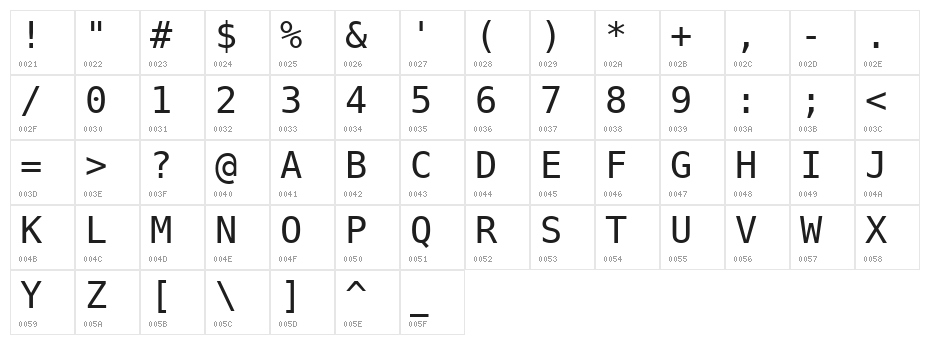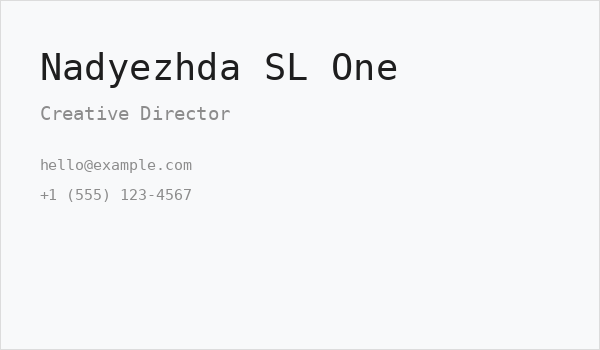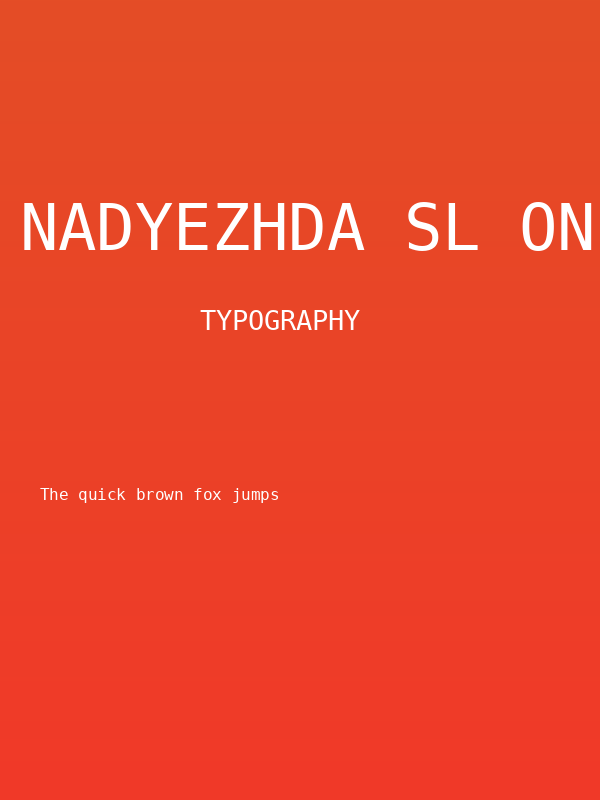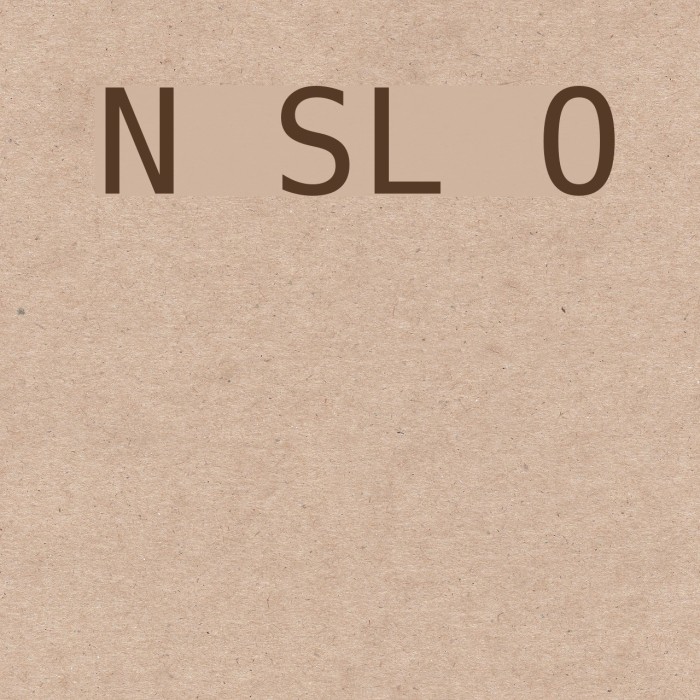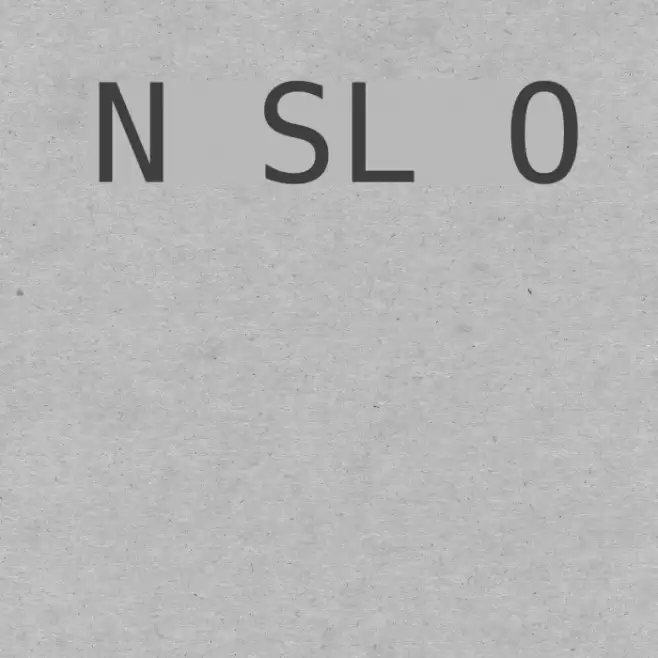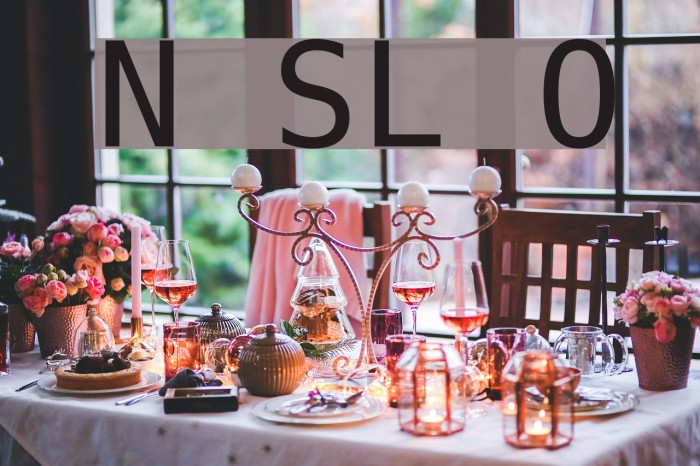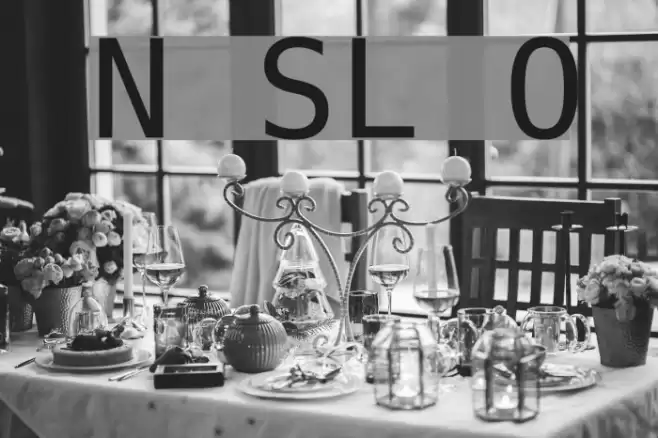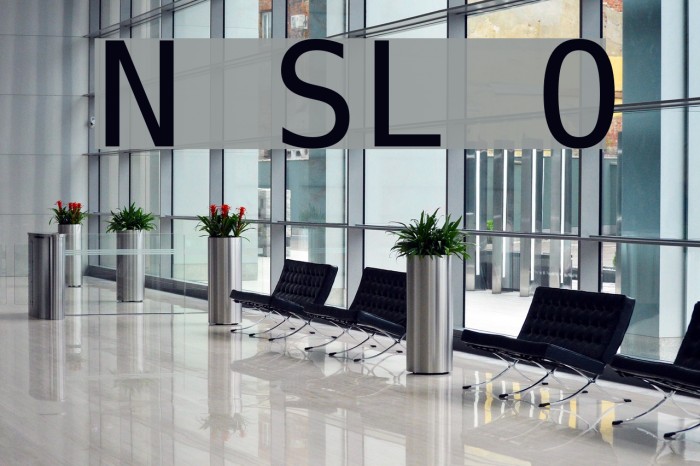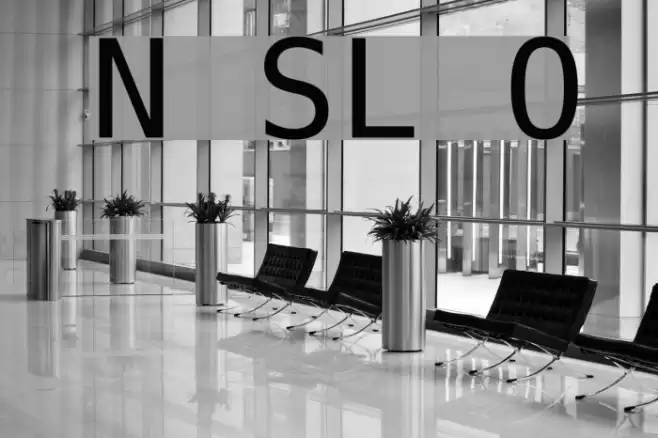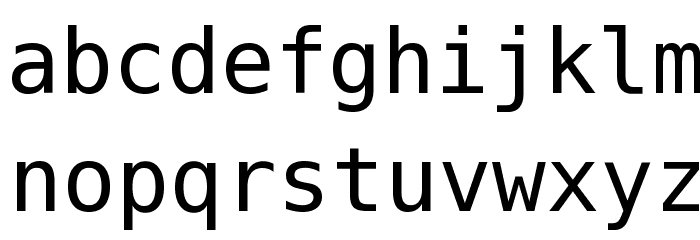
Nadyezhda SL One Font
| Anwendungsfall | Headlines, Body text, Logos |
| Vorgeschlagene Projekte | Ideal for corporate branding, web design, user interfaces, and print media where clarity and professionalism are key. |